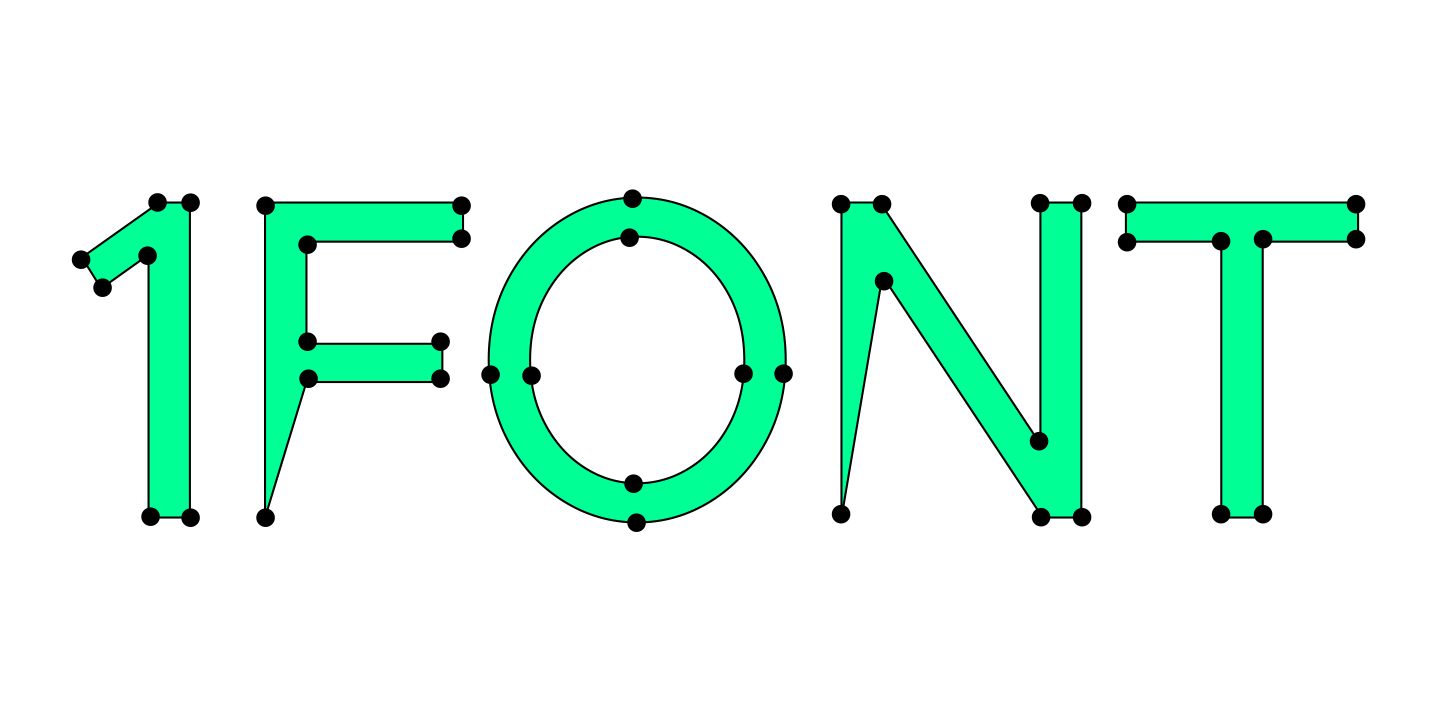
Однако именно с первой гарнитуры начинается путь шрифтового специалиста. Чтобы стать опытным дизайнером, нужно сделать первый шрифт, потом второй, третий, параллельно усваивая, какие недочёты первых этапов нужно исправлять.
Позже, когда специалист наберётся опыта, первые работы покажутся некорректными, наивными, и всё-таки вызывающими тёплую ностальгию, ведь именно с них начинался профессиональный путь.
В этой статье мы расскажем, с чего начинать разработку первой шрифтовой гарнитуры, какие программы понадобятся для работы и чему нужно уделить больше внимания.
Теоретическая подготовка
Прежде чем вы приступите к непосредственной работе, запаситесь знаниями. Этот путь похож на университетский подход: сначала лекция, уже потом практическое применение на семинарах. Впрочем, это не строгое правило, ведь кому-то легче получать знания в процессе, берясь за работу сразу и изучая конкретные вопросы, возникающие по ходу создания. Выбирайте тот путь, который подходит вам.
Среди ресурсов, которые помогут при создании шрифта, вы также можете выбрать подходящие вам. Мы рекомендуем ориентироваться на разные источники: и книги, и интернет-порталы, и трансляции специалистов.
Чем больше разных источников вы найдёте на начальных этапах, тем лучше. Позже вы сможете отсортировать их и оставить самые любимые и полезные.
Этапы создания собственного шрифта
Итак, вы вооружились знаниями и готовы приступить к работе. Вам понадобится оборудование, то есть ноутбук или компьютер, подходящая программа и желание создать самый прекрасный шрифт в мире.
Начните с постановки задачи и определения состава, стиля и характера шрифта. Для первой гарнитуры лучше выбрать минимальный кассовый состав. Ответьте себе на вопросы — можно сделать это в блокноте или текстовом редакторе:
- какой шрифт вы создаёте: гротеск, антиква, брусковый
- где может использоваться ваш шрифт: на сайте, в печатной продукции, для оформления витрин
- какое позиционирование у шрифта: ультрасовременная гарнитура для стильных проектов или классический шрифт со строгим характером, отсылающий к конкретной исторической эпохе или подходящий под определённый тренд
- в каком размере и где будет использоваться шрифт: для оформления заголовков или в приложении, в плакатах или только на сайтах
Определите сроки. Даже если вы разрабатываете гарнитуру для личного пользования, будет полезно выработать привычку работать, ориентируясь на дедлайны.
Проведите исследование. На этом этапе стоит отобрать от 3 до 10 гарнитур, близких к тому, что вы планируете разработать. Копировать их в своём проекте, конечно, не стоит, но полезно изучить графические особенности, размеры и другие параметры шрифта, чтобы понять логику построения.
Определитесь с кассовым составом. Это следует сделать ещё на первом этапе, но в этот раз вам нужно подробно выделить все знаки, которые планируете отрисовать. Это может быть один язык, например базовая латиница, цифры и набор пунктуации.
Поработайте со скетчами. Когда исследования проведены и идея будущего шрифта сформирована, приступайте к скетчам. Вы можете использовать для этого карандаш и лист бумаги, тушь и кисть или графический редактор.
Цель скетчинга — определиться с визуальными формами шрифта.
Вначале вы можете отрисовать несколько символов, чтобы наметить общие формы шрифта. Когда стиль и основные формы будут готовы, переходите к работе над конкретными буквами.
К скетчам можно обращаться, когда не можете определиться с формой какого-то глифа. Например, выбрать между двумя вариантами буквы «a». Отрисуйте несколько форм и выберите подходящую, используя скетчинг.
Отрисуйте кассу. Когда все предыдущие этапы пройдены, переходите к созданию гарнитуры в шрифтовом редакторе. Помните, что шрифт — это не отдельные буквы, а система символов, объединенных общей идеей и характером. Графические решения, составляющие стиль шрифта, должны быть логичными и повторяться в нескольких символах.
На этом этапе вам предстоит отрисовать все символы шрифта: латиницу или кириллицу, знаки пунктуации, валют, дроби, дополнительные символы. Как мы упоминали ранее, начните с простого и базового состава, чтобы закончить шрифт в запланированный срок, получить опыт и ощутить радость от завершения проекта. В последующих проектах вы сможете расширять знаковый состав.
В шрифте может быть несколько начертаний, в том числе прямые и наклонные. Начните с одного, например, Regular или Medium, самых распространённых и часто используемых.
Когда нарисованная касса будет готова, приступайте к спейсингу. На этом этапе всем буквам назначаются корректные значения для левых и правых полуапрошей, другими словами, идёт работа с расстоянием между символами.
Поработайте над технической частью. Шрифт — это не просто касса отрисованных знаков, это продукт, которым можно пользоваться в программах.
После дизайнерской части работы наступает технический этап. Именно он определяет, насколько корректно созданная гарнитура будет работать. Для первого шрифта вы можете объединиться с более опытным специалистом, который поможет с технической частью работы.
Условно этот этап состоит из трёх: мастеринг, кернинг и TrueType хинтинг.
Мастеринг — это проверка и правка контуров, компонентов, диакритики и других элементов шрифта. На этом этапе создаются OpenType фичи, заполняется метаинформация внутри шрифта.
Кернинг — это процесс, в котором расстояние между буквами приводится в безупречный вид. Проще говоря, исправляются моменты, в которых между буквами образовалось слишком много белого пространства. Этот этап происходит после того, как работа со спейсингом завершена.
Хинтинг — это визуальная разметка шрифта для корректного отображения маленьких кеглей в различных операционных системах.
Инструменты и программы для создания шрифтов
Программ для работы со шрифтами достаточно много. Вот те, которыми часто пользуются шрифтовые дизайнеры:
- Glyphs
- Fontlab
- Robofont
- FontForge
- Fontographer
Пожалуй, из этого списка можно выделить Glyphs и Fontlab, так как бо́льшая часть специалистов использует их. Это связано с удобством интерфейса, разнообразием инструментов и адаптивностью под пользователя. Студия TypeType предпочитает Glyphs, хотя раньше работа студии проходила в Fontlab.
Мы рекомендуем познакомиться с двумя-тремя разными программами, изучить их функционал и понять, в какой работа проходит наиболее комфортно. Многие программы предоставляют тестовый период, поэтому это не потребует много ресурсов.
Позже сто́ит выбрать одну программу и работать в ней, наращивая опыт и улучшая навыки шрифтового дизайна.
Заключение
Создание первой гарнитуры может вызвать страх неизвестности, ведь многим новичкам кажется, что они не справятся, а создание шрифта — это очень сложно.
Решайтесь на первый шрифт, ведь в будущем именно его вы будете вспоминать с тёплой ностальгией. Ошибайтесь, экспериментируйте, создавайте неидеальные гарнитуры и вносите в них правки — со временем вы поймёте, в каком направлении продолжать.